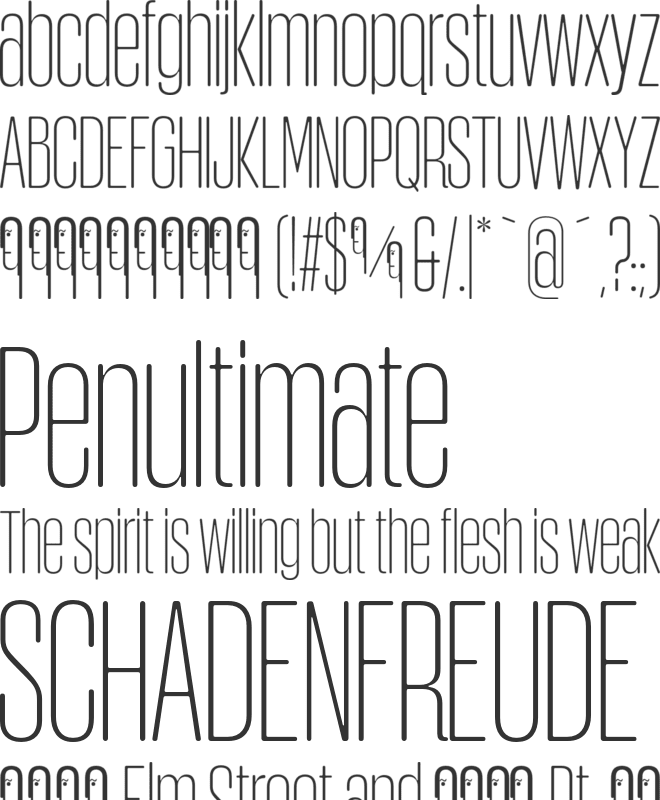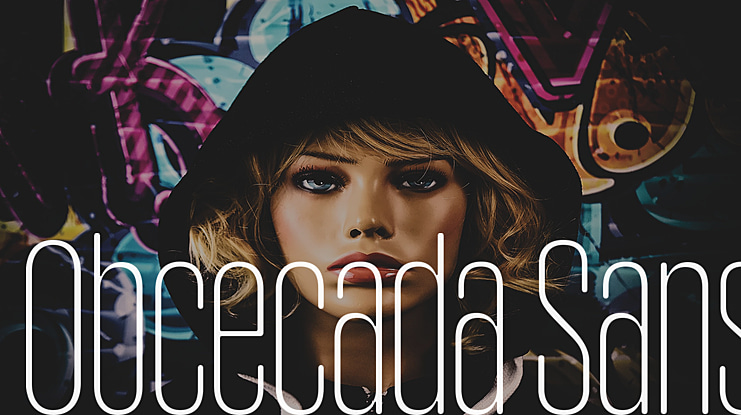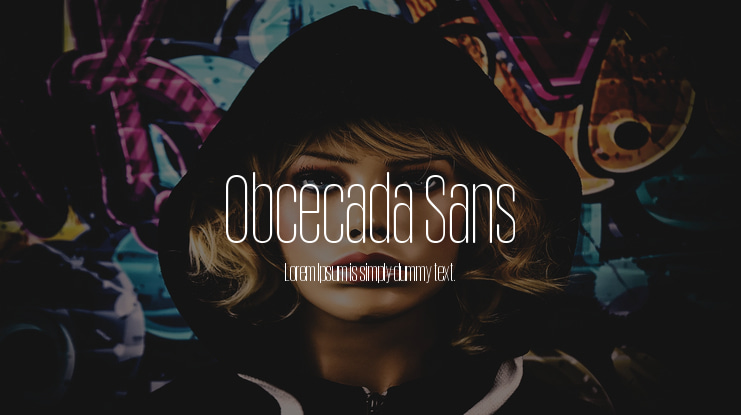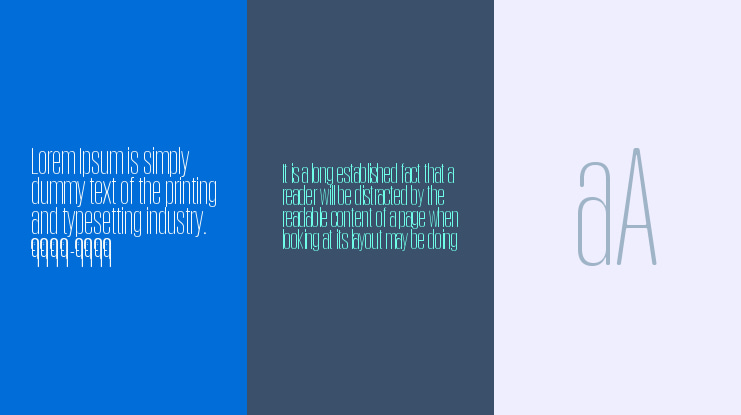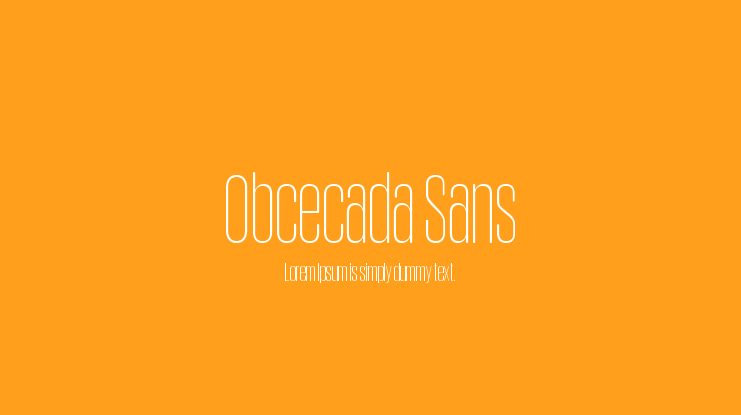
Obcecada Sans Font
Fernando Haro
Obcecada Sans es una tipografía geométrica muy condensada y fina con acabado redondeado en las astas y uniones con ascendentes y descendentes cortos. =========== Obcecada Sans is a very condensed and fine geometric typeface with rounded finish the horns and joints and falling short. =========== Descarga gratis las versión completa de la fuente desde mi web Números disponibles en mi web. Sólo para uso personal. Licencia comercial disponible + webfont